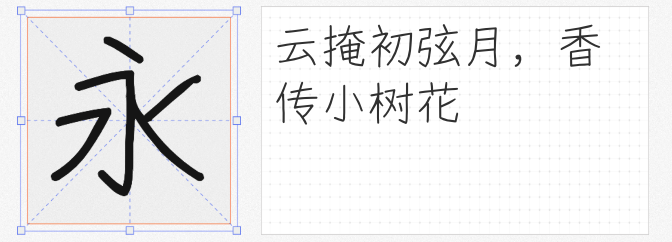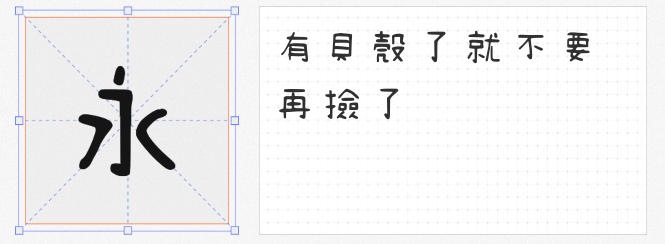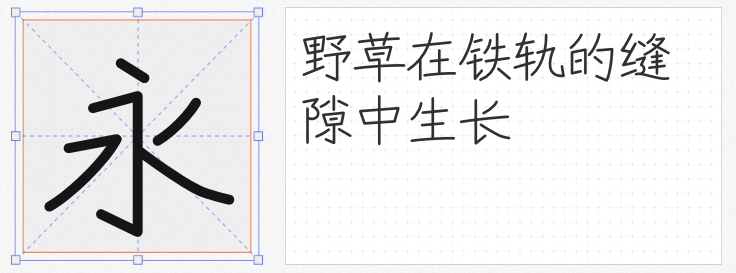
在海报设计的创意舞台上,手写字体宛如灵动的舞者,以其独特的个性和温度,为作品注入鲜活的生命力。今天为大家推荐四款免费商用且适用于海报设计的手写字体,让你的设计脱颖而出。
1. 清松手写体3
这款字体源自游清松在稿纸上的原子笔手写创作。通过“守写字”网站生成初稿字型档,再经字型软件精心后制加工而成。它保留了手写的自然痕迹,每一笔都仿佛带着书写者的温度与情感。在海报设计中运用,能营造出亲切、随性的氛围,让观众感受到那份不加修饰的真实。![]()
2. 写意体SC
以中性笔书写特性命名,写意体SC散发着独特的艺术气质。它的笔画流畅自然,既有手写的灵动,又不失规整之美。在海报里使用,能轻松平衡自由与秩序,为画面增添一份洒脱与不羁,尤其适合那些追求个性与创意的主题海报。
3. 悠哉字体 细体
基于Y.OzFont手写风格打造,悠哉字体 细体通过巧妙的拼接和调整,补全了大量汉字。它拥有丰富的字形资源,能满足各种海报设计的文字需求。字体风格悠然自得,仿佛在诉说着轻松惬意的故事,为海报带来一种闲适、自在的感觉。
4. 云峰林桥体
云峰字库出品的这款免费商用手写字体,以工整著称。一笔一划都饱含认真态度,展现出严谨的美感。在海报设计中,它能传递出专业、可靠的信息,同时又不失手写的亲和力,无论是正式场合还是轻松氛围的海报,都能完美适配。
这四款免费商用手写字体,各具特色,为海报设计提供了丰富的选择。让它们成为你创意路上的得力伙伴,共同打造出令人眼前一亮的海报作品。